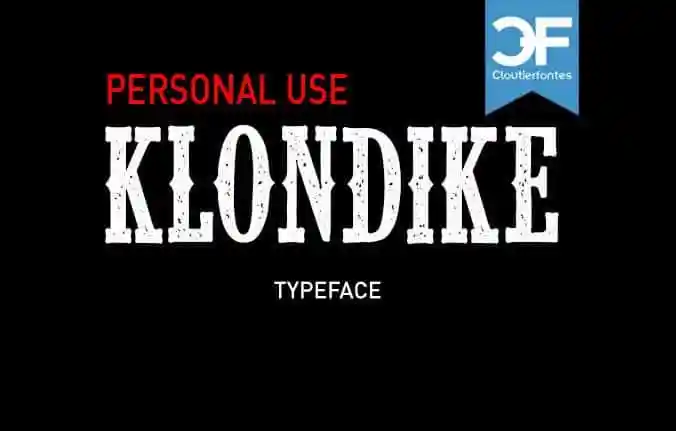
CF Klondike Typeface – Download Grátis
A Fonte CF Klondike Typeface é uma tipografia inspirada nos typewriters vintage, com linhas finas e delicadas que remetem aos tempos do computador manuseado à mão. Seu design, cuidadosamente criado por CloutierFontes, oferece um estilo retro que se adapta perfeitamente para aplicações como logotipos, materiais de marketing, ou até mesmo para desenhos artísticos modernos. Ainda que ela seja gratuitamente disponível para uso pessoal, a versão comercial é especialmente indicada para quem precisa usar o tipo em ambientes comerciais. Seja você um designer digital, um criador de conteúdo online, ou apenas alguém interessado em incorporar elementos nostálgicos à sua produção gráfica, CF Klondike Typeface se destaca como uma opção versátil e de qualidade para manusear com certa elegância.
Designer: CloutierFontes